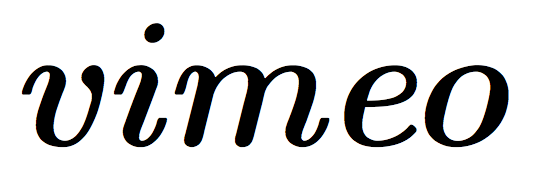
Kursive vimeo-Schrift gesucht!
hat jemand von Euch eine Ahnung um welche Schrift es sich bei dieser handelt? Für eine gewöhnliche Kursive einer Serifenschrift ist sie zu modern, zu zeitgemäß. Sie sieht wie mit einem Rollerpen gezeichnet aus. Zudem ist das kleine e recht eigenwillig – würde mich über Hinweise sehr freuen!
Für eine gewöhnliche Kursive einer Serifenschrift ist sie zu modern, zu zeitgemäß. Sie sieht wie mit einem Rollerpen gezeichnet aus.
Die Schrift ist in MetaFont gezeichnet und ist mit ziemlicher Sicherheit ein Abkömmling der Computer Modern Italic von Donald E. Knuth. Im Vergleich zur "normalen" Computer Modern wirkt die Schrift etwas gedrungen (man kann an allen möglichen Faktoren drehen) mit geringeren Strichstärkenkontrasten, dazu noch schlecht spationiert, aber die Verwandschaft der Formen ist sehr überzeugend.
Fragliche Schrift
Computer Modern Roman Italic
Die fette Computer Moder Italic kommt dem doch schon recht nahe:
Fragliche Schrift
Computer Modern Roman Bold Italic
Zur Verwendung außerhalb von TeX würde ich eher zur »Latin Modern Family of Fonts« oder kurz Latin Modern bzw. LM raten. Diese Familie ist sehr gut ausgebaut und ebenfalls frei. Die Familie umfasst zur Zeit etwa 70000 Glyphen, von denen ich hier mal ein paar angebe, die über »vimeo« hinausgehen:
Enthalten sind echte Kapitälchen (auch echte kursive Kapitälchen :) ), Serifenschrift, Serifenlose, Slabserif (proportional und dicktengleich), auch mit Kapitälchen ... besonderes Bonbönchen ist der vollständige mathematische Zeichensatz, dafür wurde der Vorgänger, Computer Modern, schließlich entwickelt.